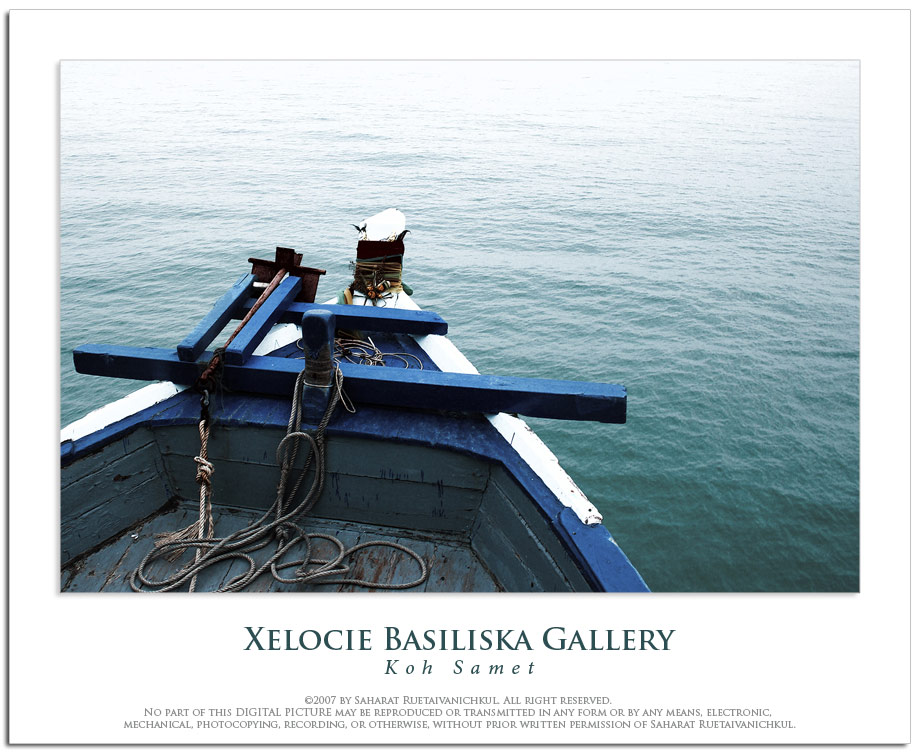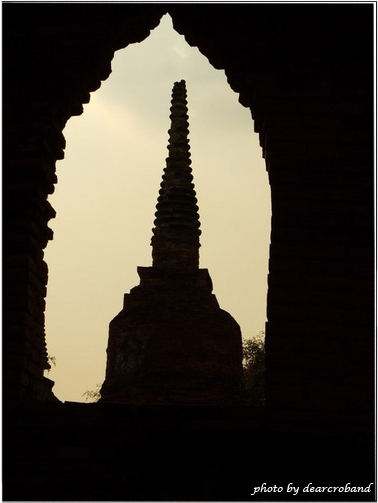
:o: การวางตัวอักษรบนภาพถ่าย :o:
ตามความคิดของผมนะครับ
ใส่นิดๆหน่อยๆพอแล้ว
เราสื่อออกไปด้วยภาพดีกว่าครับ
ใส่ตัวอักษรสีๆเยอะๆ เหมาะเอาไปทำประกอบตกแต่งเว็บอะไรพวกนี้มากกว่า
ถ้าสำหรับดูเฉยๆ หนิงชอบแบบเรียบๆมากกว่าค่ะ  ยิ้มน่ารัก
ผมทำเป็นกรอบแบบนี้ซะเลยครับ ไม่รบกวนภาพดี (หรือมันรบกวนครับ  ฮือๆ~)
น่าจะย่อๆให้ ดูได้ง่ายๆเนอะ  เกย์ออก
ลดละครับพี่เฟริน
กร๊าก ลดแบบนี้เลยเหรอ ภาพแตกหมด
(คราวหน้า Resize เหลือแค่สักไม่เกิน 600 ก็พอครับ)
บอกก่อนเลยนะครับว่ารูป "หวานเย็น" ไม่ได้ลงผิดจู๋นะครับ  ฮิ้ววว เพียงแต่อยากรู้ว่าการวางตัวอักษร 84NK บนภาพนี้เป็นอย่างไรบ้าง เห็นเขาวางกันก็เลยใช้ชื่อตัวเองวางตามบ้างครับ ช่วยชี้แนะด้วยครับ ขอบคุณครับ ไหว้
ี่ที่่ีสุดแล้วผมว่ามันอยู่ที่คนดูนะครับ  ฮิ้ววว
แบบ ก้อนขี้ก็เป็นศิลปะ
วางตัวอักษรยังไง ก็เป็นศิลปะ ต้องเข้าถึงให้ถึงแก่น  กร๊าก
ความรูปสึกแว่บแรกที่เห็นคือ ไม่รู้ว่ามันคืออะไร
อาจจะเป็นเพราะลักษณะตัวอักษรมันไม่เป็นตัวก็ได้มั้งครับ
มันก็จะสวยไปอีกแบบนะ ถ้ารู้ว่ามันชื่ออักษร 84NK ครับ
ผมทำเป็นกรอบแบบนี้ซะเลยครับ ไม่รบกวนภาพดี (หรือมันรบกวนครับ  ฮือๆ~)
ดูขรึมมากเลยครับ ทำให้ภาพมันนิ่งขึ้นเยอะ
ดูแล้วเหมือนปฏิทินเมืองนอก
ทำไมไม่ลองใส่ตัวหนังสืองุงิมั่งล่ะครับ
ผมว่ามันได้อารมณ์อีกแบบนึงดีนะ  ฮิ้ววว
ตัวหนังสืองุงิเป็นยังไงครับอยากเห็นตัวอย่างครับ  งง
แบบนี้ไง " งุงิ "  ยิ้มน่ารัก
หน้าแตก งุงิ จริงๆด้วย  หน้าแตก
:34:ใครสามารถใส่ตัวหนังสือได้โดยที่ตัวหนังสือมันไม่แย่งซีนภาพ เอามาดูหน่อยดิ๊